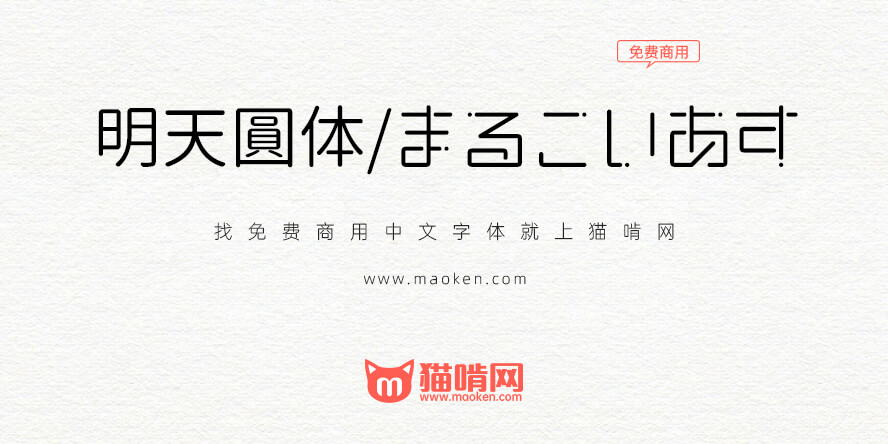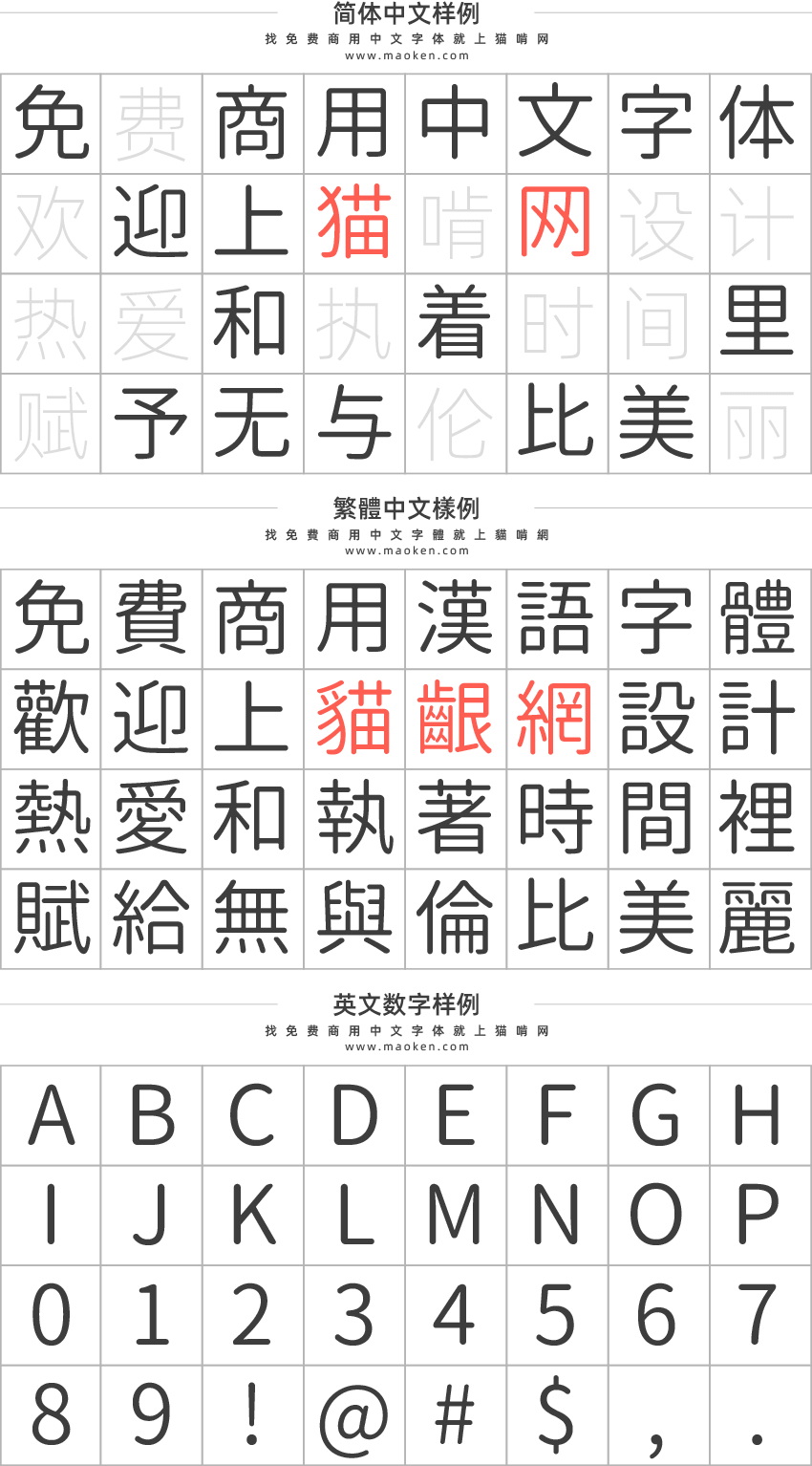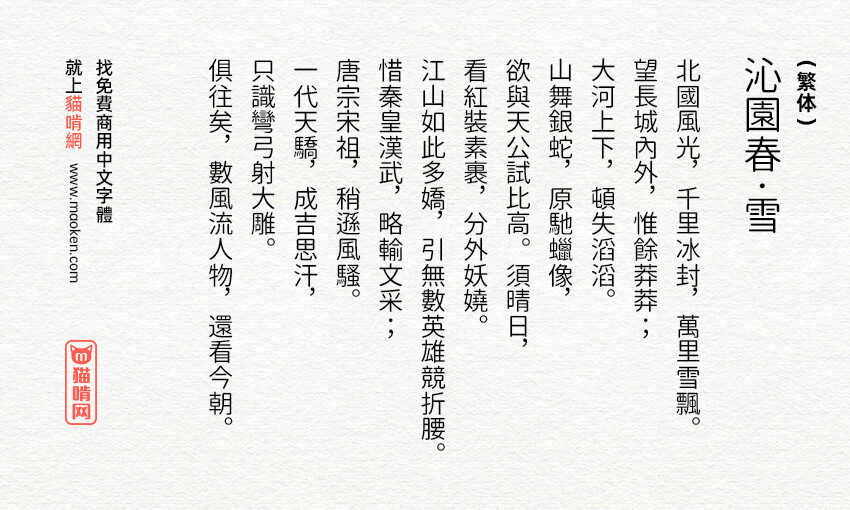
| 字体作者:あまずさ鴒 (其他语种) | 字体字重:1个 |
恋星圆体(日文名:まるこいあす)是参考漫画/动画《恋爱小行星》的logo制作的。下边缘和上边框对齐,是一种直线但圆润的字体。与“小行星”相关,还收录了表示小行星的天文符号。
- 全角数字、漢字80字を追加。「αかなのみ」作成。
- 「ト」の字形が「ド」になっていた問題を修正
- 「まるこいあす」→「α」に更新。「β」公開
- 「まるこいあす」公開
好可惜啊,看到动态投票过来的。早点看到就投这个字体的票了。如果能把繁体或者简体按照字体风格来补齐就好了
诡异的“.notdef”字符(指右侧间距调错了)
这个字体的名字应该叫“恋星圆体”的。
这个字体的作者也说的是参照了动漫《恋爱小行星》的字体样式,而《恋爱小行星》日语中叫《恋する小惑星》,其中恋爱(恋する)读作koisuru,小行星(小惑星)则采用了英语Asteroid的音译读法读作アステロイド(asuteroido)。
这款字体的名字まるこいあす,其中前两个字まる(maru)意思是“圆形、球形”,在字体中表示圆体的意思,中间两个字こい(koi)就是恋爱(恋する)的前两个音,最后两个字あす(asu)也是小行星(アステロイド)的前两个音。“こいあす”其实就是《恋する小惑星》的简称,因此这个字体名应该叫做“恋星圆体”。
有断点的字体,字体示例用断点的字体比较有代表性
这套字体本身设计(除了用源柔Gothic补全的)的汉字很少,只有134字,参见说明文档。
断线那个字体好看啊
有些字是來自源柔黑體的,都是由思源變形的!